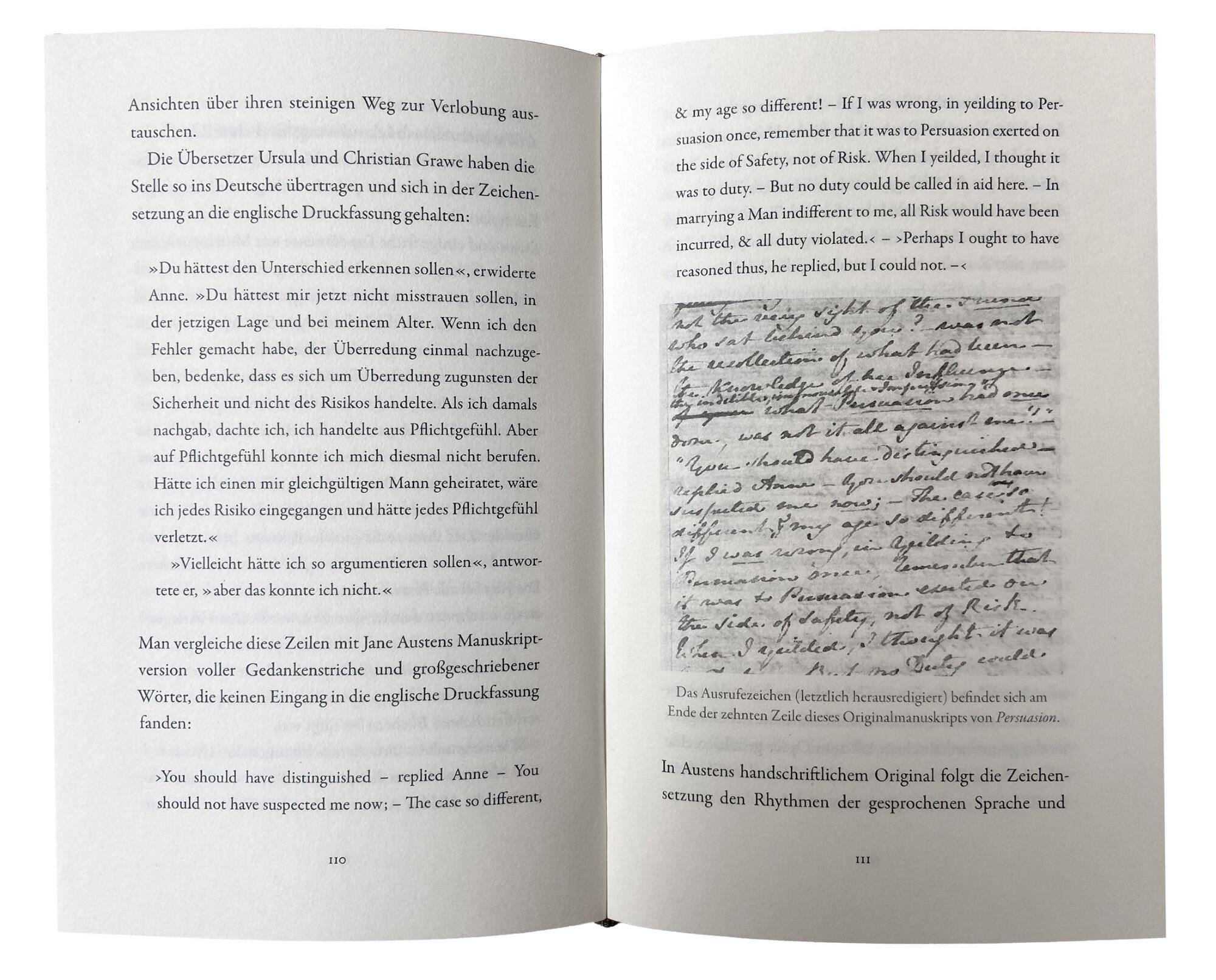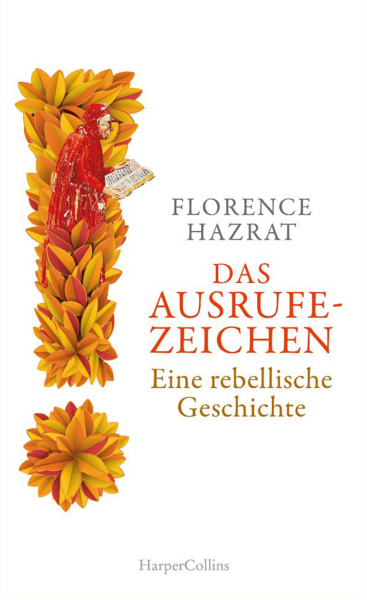
Aus der Verlagsbeschreibung:
»Kaum ein anderes Zeichen erregt unsere Gemüter wie das Ausrufezeichen. Ein Pathossymbol, das uns jubeln und wüten lässt, uns warnt und motiviert – und trotzdem wird es als »schreiendes« Symbol verkannt oder fällt populistischen Machtspielen zum Opfer.
Die Literaturwissenschaftlerin Florence Hazrat befreit das Ausrufezeichen aus den staubigen Schubladen der Grammatik und geht seiner Bedeutung als universelles, politisches und menschliches Phänomen auf den Grund. Wie konnte es sich seit seiner Erfindung vor 600 Jahren in Florenz über alle Kulturen hinweg durchsetzen? Wo hat es den Lauf unserer Geschichte entscheidend verändert, und wie prägt es unseren Alltag, unsere Kunst und Kultur bis heute? Und warum reiben sich bis heute ganze Generationen an ihm auf?
Hazrat erzählt von der Macht, Geschichte und Zukunft eines Zeichens, das es uns auf wundersame Weise ermöglicht, echte Gefühle und körperlichen Ausdruck in unsere Schriftsprache zu legen und nachzuempfinden – eine Eigenschaft, die in unseren postfaktischen Zeiten wichtiger ist denn je!
Das Buch erschien ursprünglich 2022 unter dem Titel »An Admirable Point. A Brief History of the Exclamation Mark!« über Profile Books in London. Über HarperCollins erschien 2024 eine deutsche Version, die jedoch nicht von der deutschsprachigen Autorin selbst übersetzt wurde.
Einschätzung:
Es ist interessant und erfreulich zu sehen, dass ein Element und Detail der Grammatik und Typografie in einer populärwissenschaftlichen Arbeit einer breiten Leserschaft nähergebracht wird. Das Buch trägt dabei im Prinzip alles zusammen, was es zum Thema Ausrufezeichen und der Anwendung und Erfindung von Satzzeichen im Allgemeinen zu finden war. Der Bogen spannt sich dabei von der vermuteten Erfindung des Ausrufezeichens von hunderten Jahren in Italien, über die gezielte Anwendung bei Schriftstellern, Künstlern, Werbeplakaten usw., bis hin zur übermäßigen Anwendung in Tweets von Donald Trump. Dies kann für die Leser lehrreich und unterhaltsam sein. Es fällt jedoch schwer, einen roten Faden zu finden oder das Buch überhaupt eindeutig einzuordnen. Ist es ein beschreibendes Sachbuch, eine kulturwissenschaftliche Analyse oder persönliches Plädoyer für das Ausrufezeichen? Andere Leser mögen hoffentlich mehr darin entdecken als nur »alles, was zum Ausrufezeichen zu finden war und in Buchform aneinandergereiht wurde«.